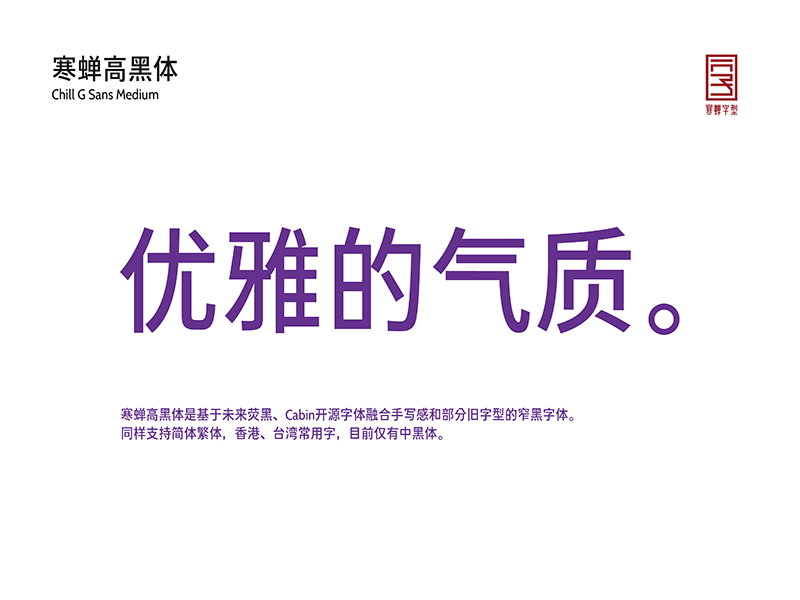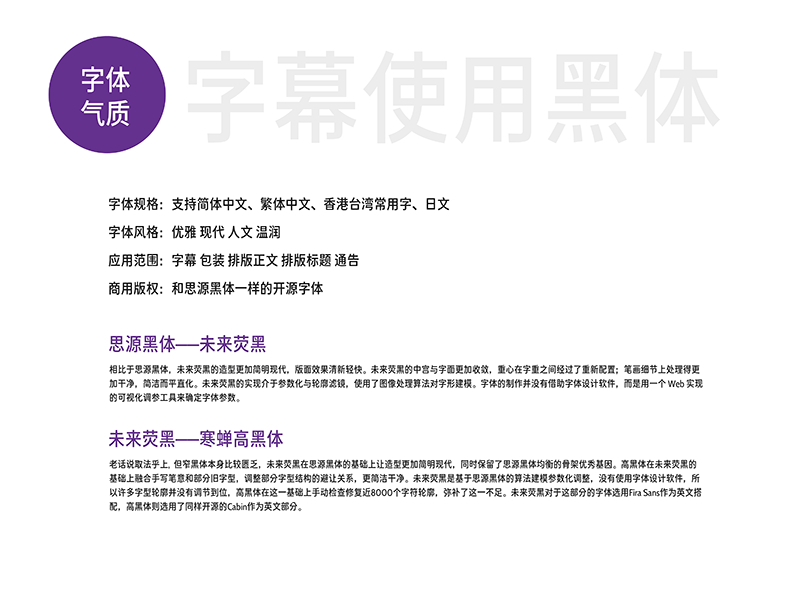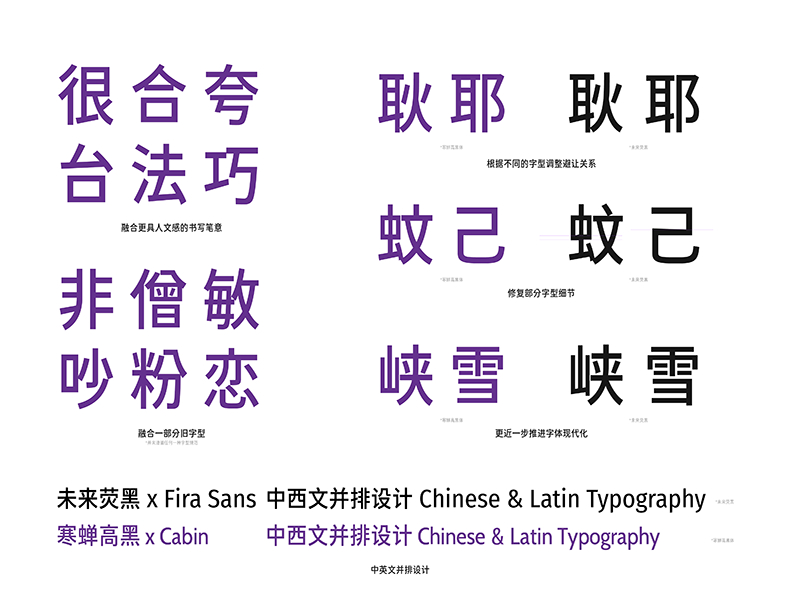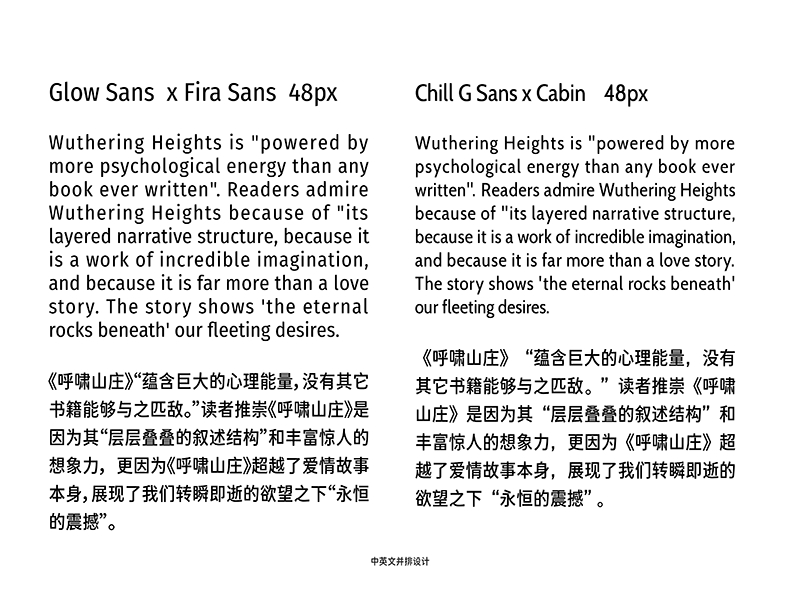
寒蟬高黑體是基於未來熒黑、Cabin開源字體融合手寫感和部分舊字型的窄黑字體。同樣支持簡體繁體,香港、臺灣常用字,目前僅有中黑體。調整了中文標點符號之間的字偶間距,避免了兩個標點符號同時使用時,產生過多空白。
字幕使用字體
字體規格:支持簡體中文、繁體中文、香港臺灣常用字、日文
字體風格:優雅 現代 人文 溫潤
應用範圍:字幕 包裝 排版正文 排版標題 通告
思源黑體——未來熒黑
相比于思源黑體,未來熒黑的造型更加簡明現代,版面效果清新輕快。未來熒黑的中宮與字面更加收斂,重心在字重之間經過了重新配置;筆畫細節上處理得更加乾淨,簡潔而平直化。未來熒黑的實現介於參數化與輪廓濾鏡,使用了圖像處理算法對字形建模。字體的製作並沒有藉助字體設計軟件,而是用一個 Web 實現的可視化調參工具來確定字體參數。
未來熒黑——寒蟬高黑
老話說取法乎上, 但窄黑體本身比較匱乏,未來熒黑在思源黑體的基礎上讓造型更加簡明現代,同時保留了思源黑體均衡的骨架優秀基因。高黑體在未來熒黑的基礎上融合手寫筆意和部分舊字型,調整部分字型結構的避讓關係,更簡潔乾淨。未來熒黑是基於思源黑體的算法建模參數化調整,沒有使用字體設計軟件,所以許多字型輪廓並沒有調節到位,高黑體在這一基礎上手動檢查修復近8000個字符輪廓,彌補了這一不足。未來熒黑對於這部分的字體選用Fira Sans作為英文搭配,高黑體則選用了同樣開源的Cabin作為英文部分。